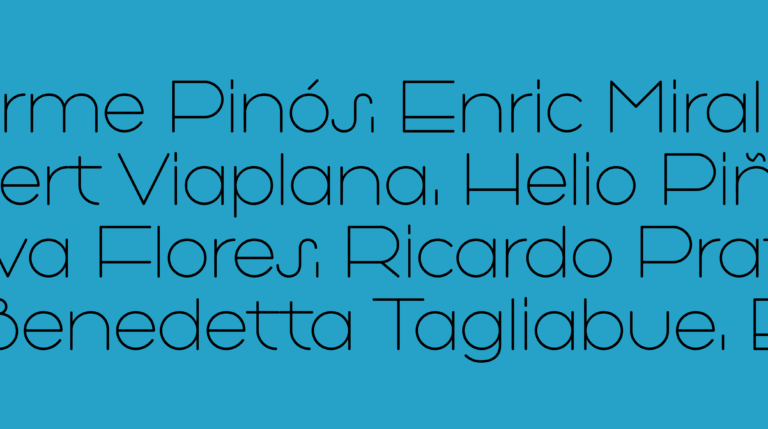
Typotheque presenta Terrassa: una tipografía que conecta la arquitectura y el diseño contemporáneo
El próximo 21 de mayo, BAU, la escuela de diseño de Barcelona, acogerá un evento que explora el vínculo entre arquitectura, geometría y tipografía. Organizado por el colectivo contraforma.barcelona y con la participación de Typotheque, la cita servirá para presentar Terrassa, una nueva tipografía diseñada por Nikola Djurek, inspirada en el lettering arquitectónico catalán del […]
Typotheque presenta Terrassa: una tipografía que conecta la arquitectura y el diseño contemporáneo
El próximo 21 de mayo, BAU, la escuela de diseño de Barcelona, acogerá un evento que explora el vínculo entre arquitectura, geometría y tipografía. Organizado por el colectivo contraforma.barcelona y con la participación de Typotheque, la cita servirá para presentar Terrassa, una nueva tipografía diseñada por Nikola Djurek, inspirada en el lettering arquitectónico catalán del […]